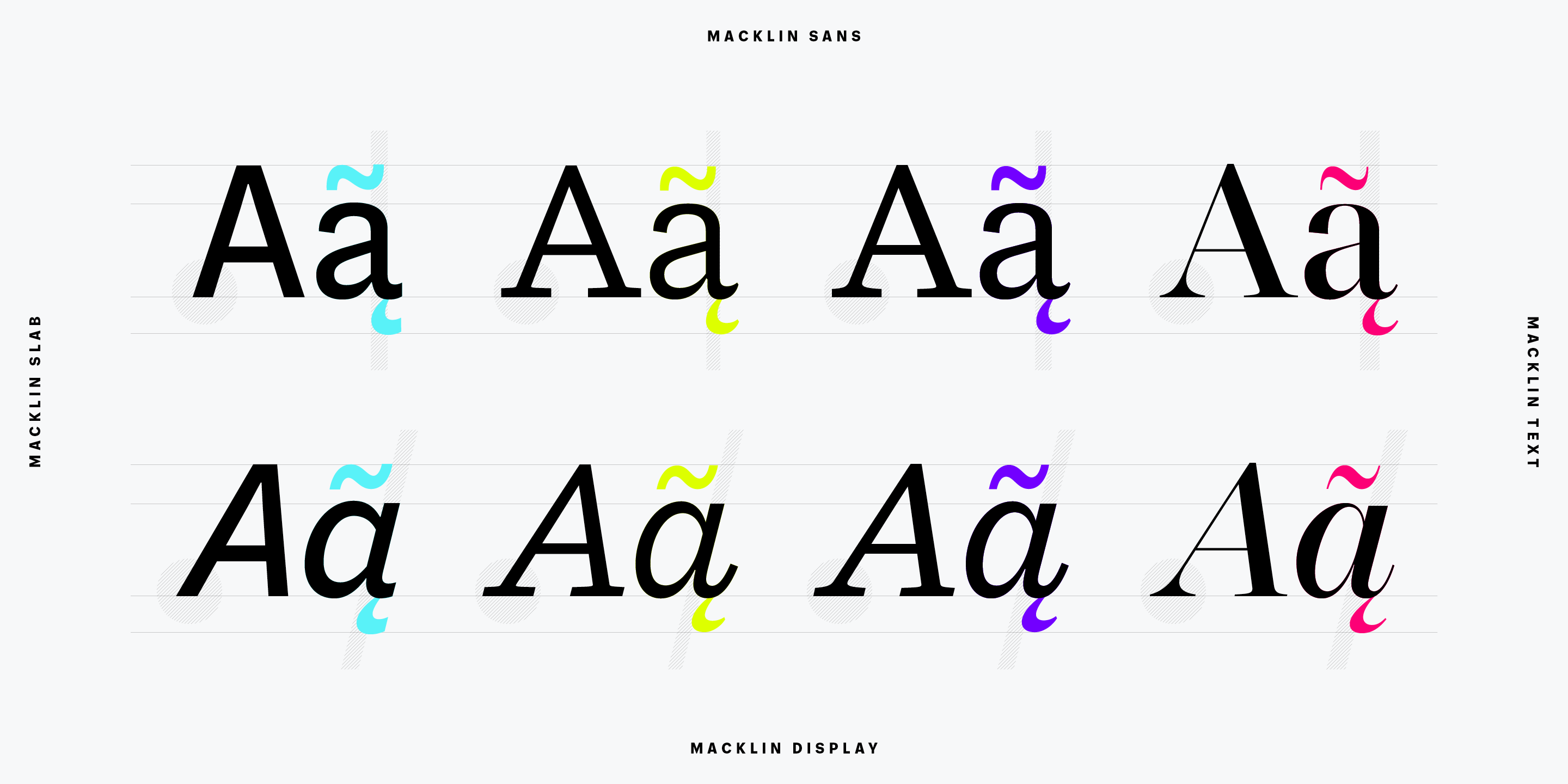
Was sind Superfamilien und warum brauchen wir sie heute?
Die Schrift hat in den vergangenen Jahrzehnten einen langen Weg zurückgelegt: von der Druckerei nebenan, wo eine Handvoll Schriftarten alle Jobs erledigten, bis zur aktuellen mobilen Kommunikation. Heute benötigen Marken und Designer einen ausgeklügelten Werkzeugkasten mit Fonts, die verschiedene Stile, Textgrößen und Sprachen bedienen. Dies hat zu einem großen Angebot an Superfamilien geführt, die eine Vielzahl von Aufgaben und Kanäle meistern können, und gleichzeitig die visuelle Identität stärken. Was genau definiert eine Superfamilie, oder eine Schriftsippe?
„Normalerweise denke ich bei einer Superfamilie als erstes, dass sie mehr als eine Stilklasse bietet, sagen wir eine Serif- und eine Sans-Variante … aber das ist nicht in Stein gemeißelt“, erklärt Terrance Weinzierl, Senior Type Designer bei Monotype. „Wenn eine Schrift viele Strichstärken und mehrere Breiten bietet, sprechen wir von einer Großfamilie. Was sie zur Superfamilie macht, ist die Fähigkeit, verschiedene Tonalitäten und Persönlichkeiten anzunehmen und gleichzeitig selbstidentisch zu bleiben … durch ein gemeinsames Buchstabengerüst, sowie synchrone Strichstärken und Metriken.“
Versuchen wir dies einfach mal mit einem anderen grafischen Grundbaustein zu illustrieren, der Farbe. Während eine große Schriftfamilie, quasi eindimensional, die Achse von einem hellen bis hin zum dunklen Blau abdecken kann, bringt die Superfamilie ein zweite Dimension ins Spiel, und erlaubt zum Beispiel die Erweiterung des Farbraums von Grün-Blau bis hin zu gelblichen und violetten Schattierungen. Superfamilien ermöglichen den Designern, verschiedene Schriftstile in einem 2-oder 3-dimensionale Schriftstilraum zu wählen und harmonisch zu kombinieren, ohne selbst nach optisch verwandten Schriften recherchieren zu müssen.
Malou Verlommes neue Superfamilie Macklin ist ein gutes Beispiel für eine zeitgemäße Superfamilie, da sie sowohl zwei Schriftklassen als auch zwei Anwendungsbereiche in einer einzigen Familie vereint: Sans & Slab und Text & Display (zwei optische Größen). Da die vier Familien auf einer gemeinsame Architektur basieren, harmonieren sie alle miteinander.
Ein Komplettbaukasten für Marken.
Gerade diese innere Harmonie ist es, was Superfamilien für das Marketing so wertvoll macht. Sie erlauben Unternehmen oder Marken, sich für nur eine Schrift zu entscheiden, die aber alle kreativen Aufgaben meistern kann und darüber hinaus dem Design-Team Räume für zukünftige Anpassungen öffnen.
Superfamilien können unter anderem im Editorial Design sehr hilfreich sein, wo Sans und Serifs miteinander und nicht gegeneinander antreten. Oder in Firmen, die eine Monospaced- Variante ihrer Hausschrift für Angebote, Rechnungen und den Geschäftsbericht benötigen. Marken, die neue Produkte auf den Markt bringen, ihren Geschäftsbereich ausdehnen oder sich auf neuen Plattformen präsentieren möchten, brauchen einen flexiblen typografischen Baukasten … zum Beispiel eine Superfamilie, die bei allen Auftritten in die visuelle Identität der Marke einzahlt.
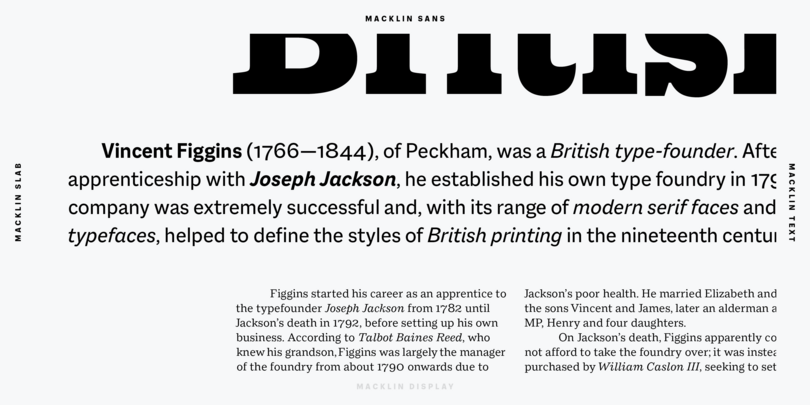
This image shows how three styles of Macklin—Slab for the headline, Sans for the subhead, and Text for the body—can be used to lay out a single editorial piece. Superfamilies like this give you the range to distinguish different blocks of text while maintaining a strong visual throughline.
„Eine Superfamilie in Ihrem Styleguide hilft dabei, eine neue Produktlinie zu promoten, einen neuen Service bekannt zu machen oder den Tonfall Ihres Unternehmens zu reformieren, garantiert authentisch und wiedererkennbar“, hebt Weinzierl hervor.
„Stellen wir uns ein Möbelunternehmen vor, das eine Produktlinie fürs Kinderzimmer starten möchte“, ergänzt Weinzierl. „Die Hauptmarke verwendet eine Sans, für die neue, junge Linie kommt eine Rounded-Version dieser Schrift zum Einsatz. Die sieht freundlich aus, fügt sich sicher in den Workflow ein und harmoniert automatisch mit der Marke. Gerade hier kommt es darauf an, eine eng benachbarte Schrift zu finden, keine kontrastierende.
Terrance Weinzierl.
Manche Superfamilien bieten eine derart große Auswahl an Schriftvarianten, dass es einem Design-Team schwer fallen kann, den Anfang zu finden. „Wer sich von dem Angebot überfordert fühlt“, rät Weinzierl, „sollte klein anfangen, von innen nach außen“. Der Start mit einem klassischen Set an Strichstärken (z. B. Regular, Medium, Bold, Black) und eventuell den passenden Kursiven dazu ermöglicht es allen Benutzern, sich langsam mit der Familie vertraut zu machen. Es gibt den Designern ausreichend Zeit zu verstehen, wohin sich ein Projekt entwickeln könnte, ob es weiterer Stile bedarf oder eines größeren Kontrasts. Das Lizenzieren einer kleinen Palette, die jederzeit schrittweise erweitert werden kann, ist perfekt für Start-ups oder Designer, die in der Frühphasen einer Markenentwicklung stecken und deren Budget limitiert ist.
„Superfamilien sind gerade n der Anfangsphase eines größeren Projektes hilfreich, wenn noch nicht klar ist, was eine Marke in Zukunft braucht“, sagt Weinzierl. „Nehmen wir an, Sie arbeiten an einem Packaging-Konzept, bei dem noch völlig offen ist, wie breit das Produktspektrum mal werden könnte, aber es sollen erste Prototypen gebaut werden. Wenn Sie mit einer Superfamilie starten, bauen sie eine flexible typografische Basis, deren Tonalität sie leicht ändern können, ohne das gesamte Layout über den Haufen zu werfen. Später dient eine Superfamilie der Langlebigkeit einer Marke, und erweist sich somit als nachhaltige Investition.“
„Steht Ihnen eine Sans, eine Serif und eine Rounded zur Verfügung, und Sie wissen noch nicht, wofür Sie welchen Stil einsetzen sollen … betrachten Sie es wie eine Rücklage für die Zukunft: Die Schrift als Speisekammer“, scherzt Weinzierl. „Mit dieser Strategie können Sie in ein paar Jahren, wenn eine Untermarke oder ein neues Produkt lanciert werden soll, auf das inzwischen erzielte Renommee und die visuelle Bekanntheit der Marke aufbauen. Sie profitieren automatisch von der typografischen Bandbreite, mit der Sie klein angefangen haben“.
„Da unsere Computer sowie das gesamte Design und das Coding drumherum immer komplexer und verwobener werden, stellt sich die Frage, wie wir die Tonalität innerhalb einer bestehenden Architektur nur ,ein klein bisschen‘ abändern können“, sagt Weinzierl. „Kann die Schrift an dieser Stelle nicht gerundet sein? Könnten Serifen bei den Bildunterschriften nicht die Lesbarkeit verbessern? Einschränkungen werden zu Chancen, weil alles machbar ist“.